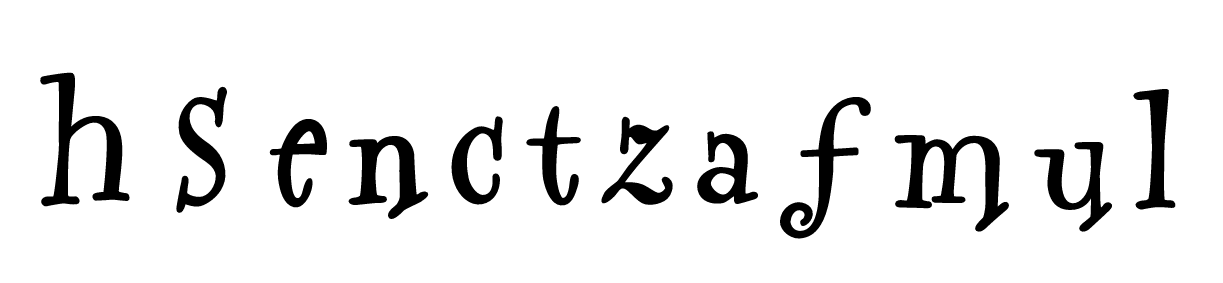
Lustige Antiqua mit schrägen Serifen
Schrift stammt von einem Logo und liegt in Kurven vor,
mehr Buchstaben habe ich leider nicht.
Das Logo ist ca. 8–10 13 Jahre alt, dürfte also kein neuer Font sein.
Ich vermute einen Freefont, bin mir aber nicht sicher, einen
handgemachten Schriftzug schließe ich aus.
das original ist ein etikett. aber die quelle ist in diesem fall auch uninteressant, die kann in diesem fall auch nicht weiterhelfen. die buchstaben die im schriftzug vorkommen sind alle abgebildet, mehr gibts da leider nicht. was ähnliches nützt mir nicht.
...  einen
handgemachten Schriftzug schließe ich aus.
Und ich schließe entschieden aus, dass der Schriftzug nicht irgendwann handgemacht ist,  denn auch die Glyphen eines Fonts sind ja irgendwann einmal handgemacht, selbst wenn die Glyphen dann mithilfe eines Vektorisierungs-Programms in den Font gekommen sein sollten.
Vielleicht ändert sich das ja irgendwann, und man sagt dem Computer nur noch: "Erstelle mir eine Schriftart, mit lustig schiefen  Serifen", der Computer beginnt, beobachtet dabei den Gesichtsausdruck seines Besitzers, und wenn der bis zu den Ohrläppchen zu grinsen beginnt, ist der Font ohne Handarbeit fertig - aber das wird wohl noch ein paar Wochen dauern :-)